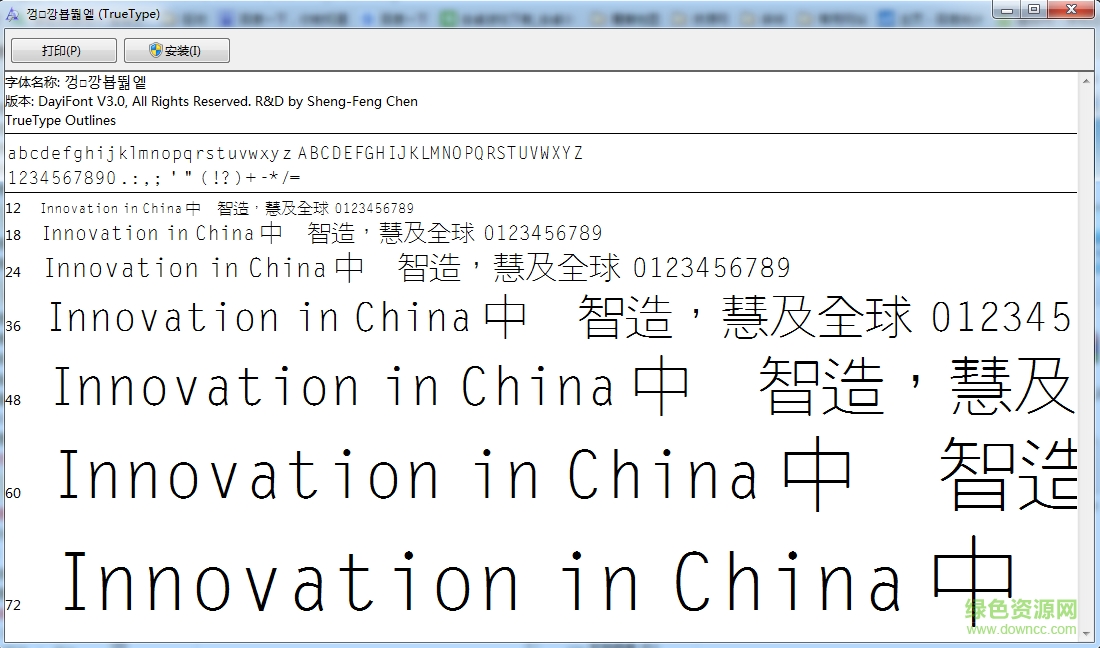
[dath1]字體又叫書(shū)法家線黑體,是一款富含人文氣息的書(shū)法字體,結(jié)構(gòu)簡(jiǎn)單、純粹,筆畫(huà)寬狹設(shè)置合適,細(xì)節(jié)特征設(shè)計(jì)到位,給人非常干凈的美感享受,需要的朋友快來(lái)綠色資源網(wǎng)下載吧!